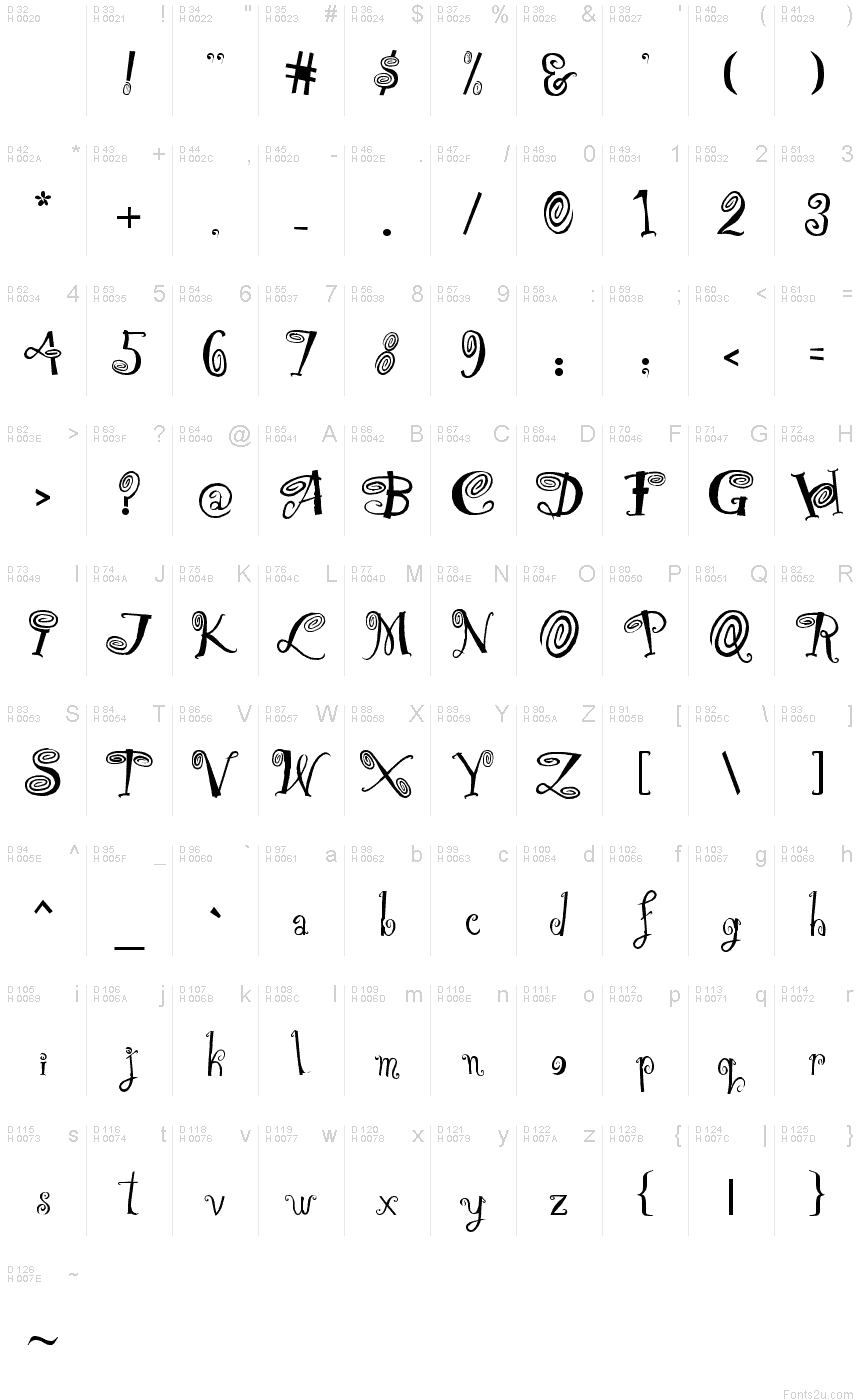
HipnOtik autorstwa Randy'ego Forda to darmowy, ozdobny krój pisma o dzikim, odręcznym charakterze. Wysokie, lekko przekrzywione litery sprawiają wrażenie, jakby tańczyły na linii, a zawijane kształty wyglądają, jakby zostały naszkicowane czarnym markerem. Nieregularne kąty i zabawne zawijasy nadają całości lekko upiorną, cyrkową energię, która natychmiast przyciąga wzrok do środka projektu.
Używając HipnOtik, możesz dodać dramatyzmu plakatom na Halloween, zaproszeniom na imprezy, okładkom zinów, ulotkom zespołów indie, opakowaniom produktów czy nietuzinkowym grafikom do mediów społecznościowych. Ten darmowy font świetnie sprawdza się w dużych rozmiarach, pozwalając wyeksponować krzywe i spirale; w tekście głównym połącz go z prostym, neutralnym krojem bezszeryfowym, aby zachować czytelność przy zachowaniu śmiałego stylu.